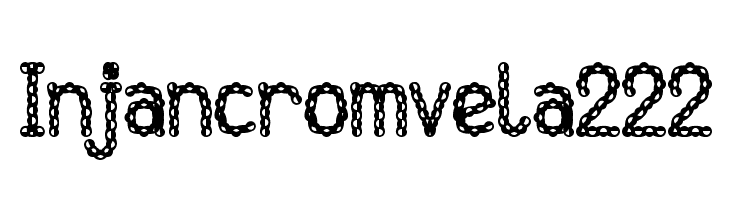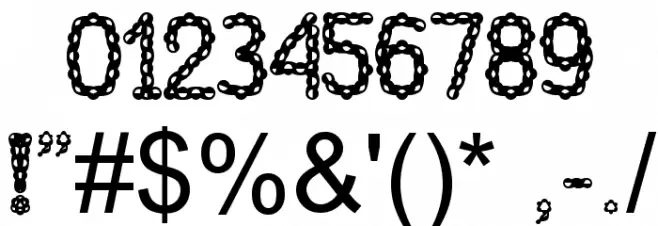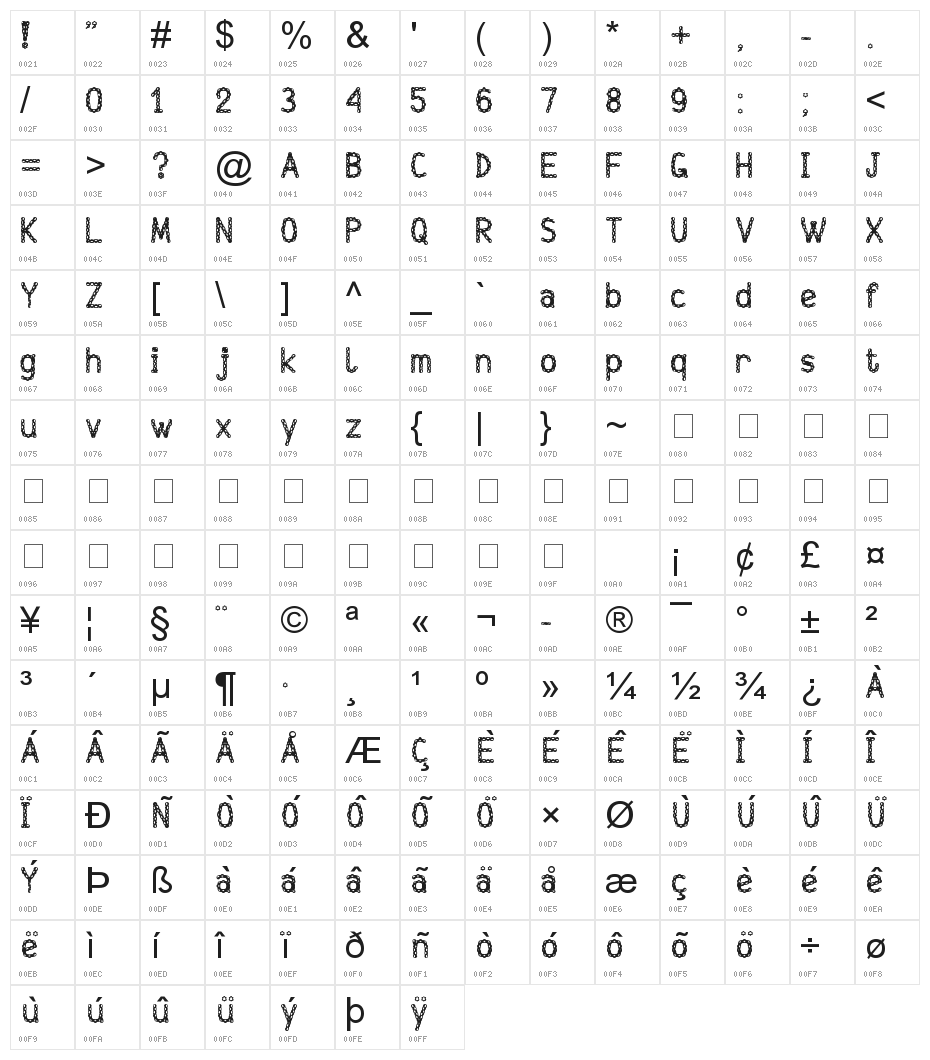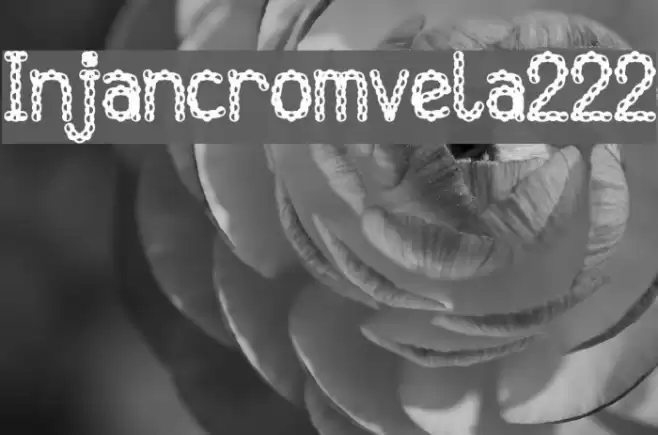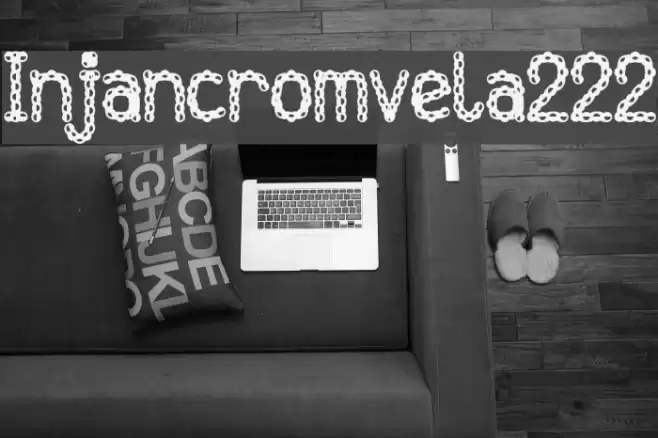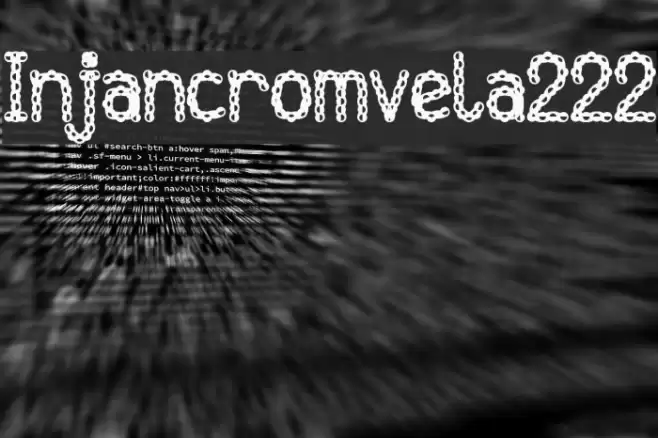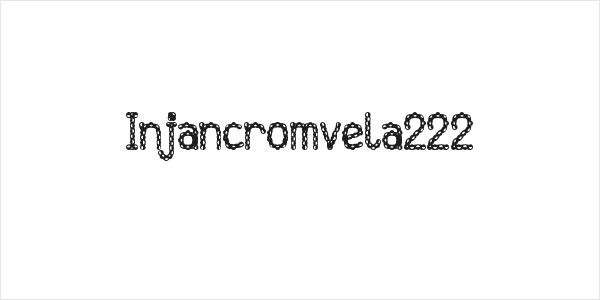
Injancromvela222 Font
| Категория | Decorative |
| Область применения | Logos, Posters, Invitations |
| Рекомендуемые проекты | Ideal for creative projects such as posters, invitations, and branding that require a playful and distinctive look. |